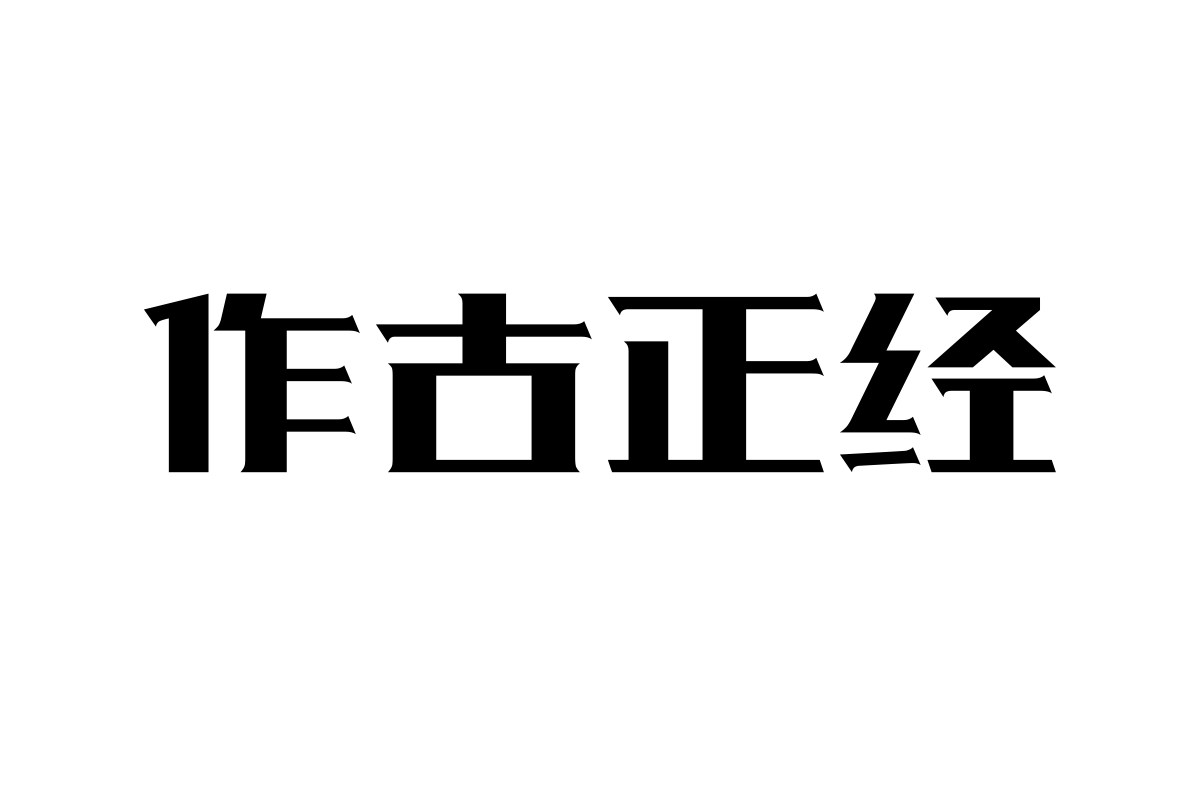
上首星芒体是一种具有现代感和科技感的字体,它的特点在于其独特的星芒效果。这种字体在设计时采用了特殊的排版方式,使得每个字母都呈现出一种独特的光泽感,仿佛星星在闪烁。同时,这种字体还具有一定的艺术性,能够吸引人们的眼球,提升整体的设计效果。
上首星芒体的笔画粗细适中,线条流畅,既有力量感又不失优雅。它的结构紧凑而有力,每一个字母都充满了动感和生命力。无论是在文字排版还是图形设计中,都能够展现出独特的魅力。
总的来说,上首星芒体是一种非常具有现代感和科技感的字体,它能够为设计作品增添一份独特的韵味和视觉冲击力。